Johannes Gutenberg, nazywany po polsku Janem Gutenbergiem, jest uznawany za jednego z najważniejszych wynalazców w historii ludzkości. Opracowana przez niego technologia druku z ruchomych czcionek zrewolucjonizowała przekazywanie wiedzy, przyspieszyła rozwój nauki i przyczyniła się do upowszechnienia książek na niespotykaną wcześniej skalę.
W rankingach najważniejszych osiągnięć cywilizacji wynalazek Gutenberga często znajduje się obok elektryczności, komputera czy internetu. Wielu historyków uważa wręcz, że bez mechanizacji druku nie byłby możliwy rozwój nowoczesnej nauki, edukacji i kultury.
Johannes Gensfleisch zur Laden, znany dziś jako Jan Gutenberg, urodził się w Moguncji około 1397 roku. Pochodził z rodziny związanej z rzemiosłem metalowym i już od młodości zdobywał doświadczenie w obróbce metalu, grawerowaniu oraz wykonywaniu precyzyjnych elementów użytkowych.
Przez pewien czas mieszkał w Strasburgu, gdzie zajmował się między innymi szlifowaniem kamieni szlachetnych i nauczaniem rzemiosła. Największą pasją Gutenberga były jednak eksperymenty związane z drukiem oraz sposobami powielania tekstów.
W tamtych czasach wszystkie książki były przepisywane ręcznie przez skrybów. Proces ten był niezwykle powolny, kosztowny i podatny na błędy.
Przed XV wiekiem każda książka była kopiowana ręcznie. Przepisanie jednego egzemplarza Biblii mogło zająć wiele miesięcy, a nawet kilka lat pracy.
W rezultacie książki były bardzo drogie i dostępne głównie dla klasztorów, uniwersytetów oraz najbogatszych osób.
Powszechna edukacja praktycznie nie istniała, ponieważ niewiele osób miało dostęp do źródeł wiedzy.
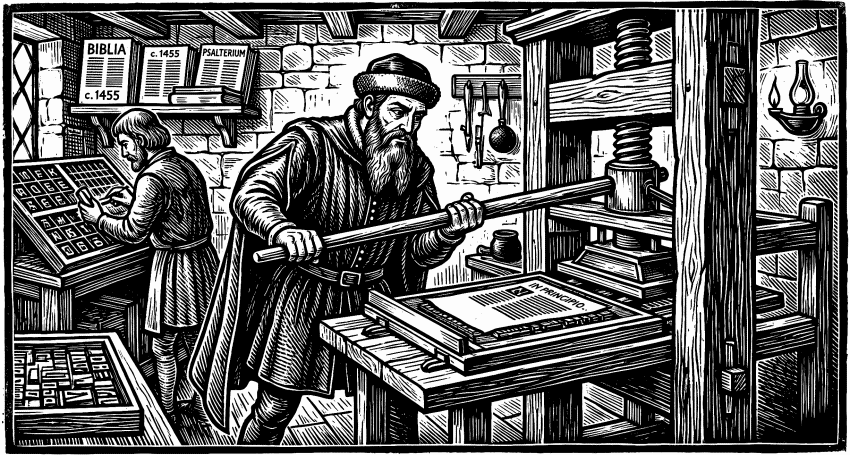
Największym osiągnięciem Gutenberga było opracowanie praktycznego systemu druku wykorzystującego ruchome metalowe czcionki.
Wcześniej stosowano już różne techniki odbijania tekstów, jednak były one mało wydajne lub nie pozwalały na łatwe składanie nowych publikacji.
Gutenberg połączył kilka technologii:
Dzięki temu możliwe stało się wielokrotne wykorzystywanie tych samych liter do drukowania kolejnych stron.
Każda litera była osobnym metalowym elementem. Zecer układał z nich wyrazy, zdania i całe strony tekstu.
Po wydrukowaniu strony czcionki można było rozłożyć i wykorzystać ponownie do złożenia następnej publikacji.
Takie rozwiązanie pozwalało drukować setki identycznych egzemplarzy książki znacznie szybciej niż przy ręcznym przepisywaniu.
To właśnie ruchoma czcionka stała się fundamentem nowoczesnej typografii i drukarstwa.
Najbardziej znanym dziełem Gutenberga jest tzw. Biblia Gutenberga, wydrukowana około 1455 roku. Była to jedna z pierwszych dużych książek wykonanych przy użyciu ruchomych czcionek. Egzemplarze zachwycały jakością wykonania. Litery były równe, strony identyczne, a całość prezentowała się niezwykle elegancko.
Dla współczesnych ludzi był to prawdziwy technologiczny przełom.
Do dziś zachowane egzemplarze Biblii Gutenberga należą do najcenniejszych druków świata i osiągają zawrotne ceny na aukcjach.
Masowy druk sprawił, że książki zaczęły być dostępne dla znacznie większej liczby ludzi.
Przyczyniło się to do:
W ciągu kilkudziesięciu lat od wynalazku Gutenberga drukarnie zaczęły powstawać w całej Europie.
Jan Gutenberg zmienił sposób przekazywania wiedzy bardziej niż większość wynalazców w historii. Dzięki ruchomej czcionce książki przestały być dobrem dostępnym wyłącznie dla nielicznych, a wiedza mogła rozprzestrzeniać się szybciej niż kiedykolwiek wcześniej. Współczesne fonty komputerowe i cyfrowa typografia są bezpośrednimi spadkobiercami technologii, którą Gutenberg zapoczątkował w XV wieku.
Przez kolejne stulecia technologia druku była stale rozwijana. Metalowe czcionki wykorzystywano aż do XX wieku.
Prawdziwa rewolucja nastąpiła dopiero wraz z pojawieniem się komputerów oraz cyfrowych fontów.
Dzisiejsze czcionki zapisane są w postaci plików komputerowych i mogą zawierać tysiące znaków, ligatur, kapitalików oraz rozbudowane funkcje typograficzne.
Mimo ogromnych zmian technologicznych współczesna typografia nadal opiera się na zasadach zapoczątkowanych przez Gutenberga ponad pięćset lat temu.
Za twórcę pierwszej praktycznej technologii druku z ruchomych metalowych czcionek uznawany jest Johannes Gutenberg.
Przyjmuje się, że jego przełomowe prace prowadzono w pierwszej połowie XV wieku, a Biblia Gutenberga została wydrukowana około 1455 roku.
Był to pojedynczy metalowy znak, który można było wielokrotnie wykorzystywać do składania różnych tekstów.
Jest uznawana za jedno z najważniejszych dzieł w historii drukarstwa i symbol początku epoki druku.
Nie. Techniki drukarskie były znane wcześniej, szczególnie w Azji. Gutenberg jako pierwszy stworzył jednak praktyczny system wykorzystujący ruchome metalowe czcionki na szeroką skalę.
Stworzył podstawy nowoczesnego składu tekstu, drukarstwa i projektowania krojów pisma, które rozwijane są do dziś.